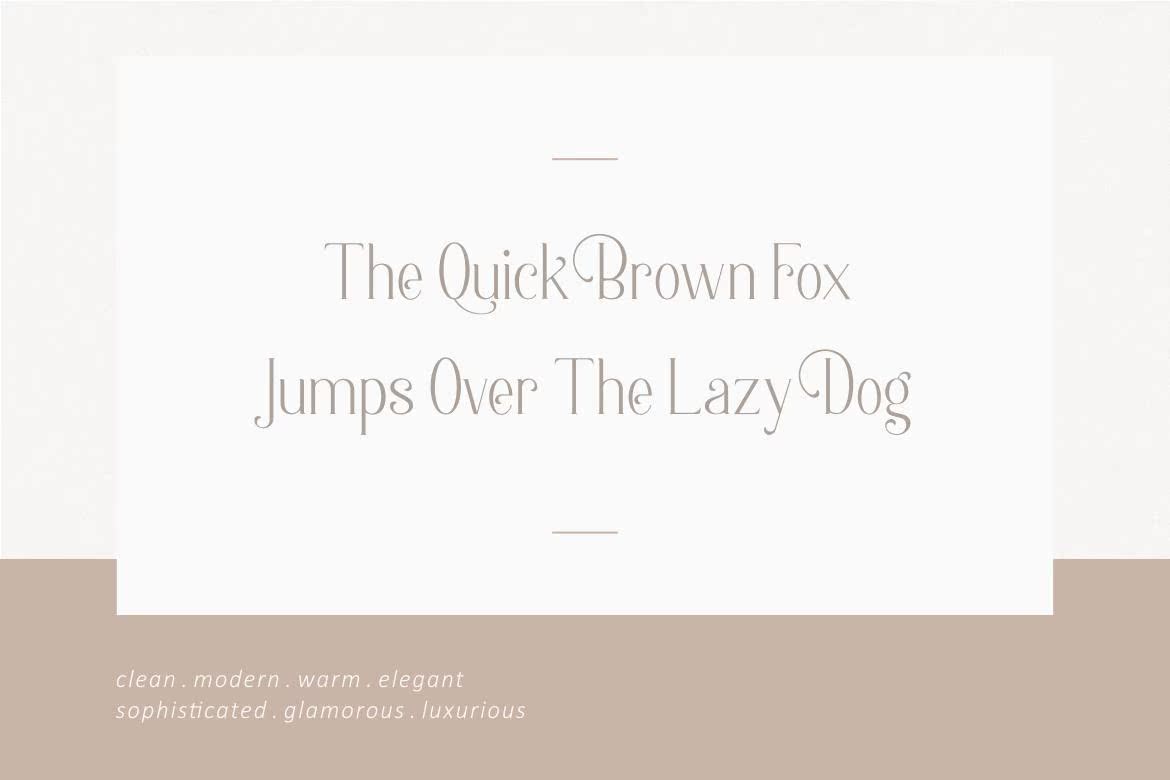
BerlincollectionFontisanelegant系列以完整和高精度的方式设计,以创建一个简单的字体样式。它以现代和最低的方式完美地呈现一个灵活的屏幕。BerlincollectionFontisanelegant系列以完整和高精度的方式设计,以创建一个简单的字体样式。它以现代和最低的方式完美地呈现一个灵活的屏幕样式